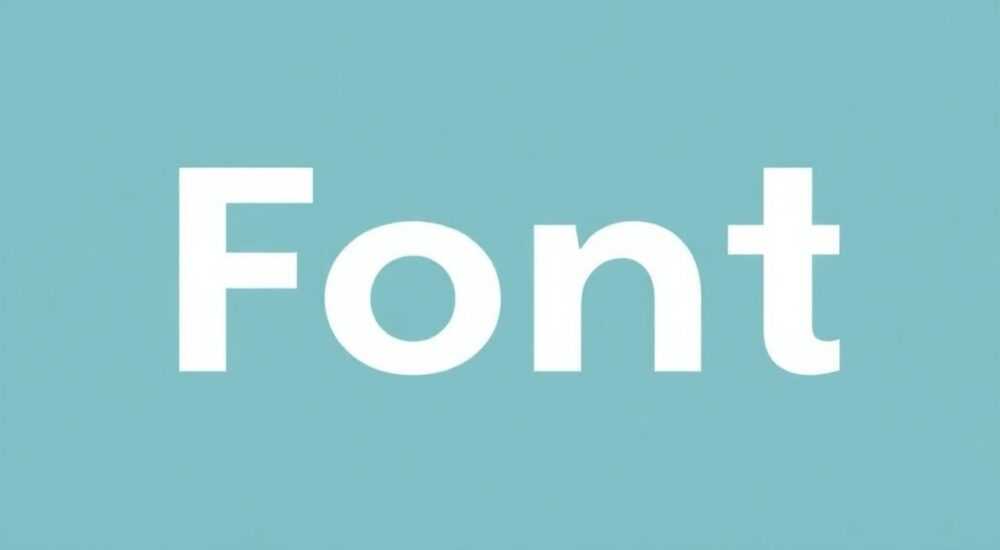
Как в фотошопе поменять шрифт
Изменение шрифта в Photoshop — одна из базовых, но крайне важных операций при работе с текстом на изображениях. Будь то редактирование баннера, создание макета для соцсетей или корректировка дизайна логотипа, умение быстро и точно заменить шрифт позволяет сохранить целостность визуального стиля. В отличие от простых графических редакторов, Photoshop предоставляет полный контроль над типографикой: от выбора гарнитуры до тонкой настройки интерлиньяжа и кернинга.
Основные шаги: как поменять шрифт в Photoshop
Замена шрифта в Photoshop начинается с правильного выделения текстового слоя. Откройте файл в программе и перейдите в палитру «Слои» (F7). Найдите слой с текстом — он будет обозначен значком «T» и называться, например, «Text» или содержать фрагмент текста. Дважды щелкните по этому слою, чтобы активировать режим редактирования.
Выберите инструмент «Текст» (горячая клавиша T). Кликните внутри текстового блока на холсте, чтобы появился текстовый курсор. В этот момент в верхней панели параметров активируется строка настройки шрифта. Здесь вы увидите выпадающий список с текущей гарнитурой.
Чтобы изменить шрифт, просто кликните по названию текущей гарнитуры и пролистайте доступные варианты. Вы можете начать вводить название шрифта вручную — Photoshop поддерживает поиск по имени. После выбора нового шрифта текст на холсте обновится мгновенно.
- Убедитесь, что текстовый слой не растрирован — иначе его нельзя будет редактировать как текст.
- Используйте сочетание Ctrl+Z (Cmd+Z на Mac) для отмены, если шрифт сместил разметку.
- Проверьте размер шрифта и межбуквенные интервалы — они могут меняться при смене гарнитуры.
Если текст состоит из нескольких абзацев или использует разные стили (жирный, курсив), выделите только ту часть, которую хотите изменить. Для этого зажмите Shift и выделите нужные символы мышью. Это особенно полезно при работе с заголовками и подзаголовками.
Пошаговая инструкция
- Откройте PSD-файл в Photoshop.
- Перейдите в палитру «Слои» и найдите текстовый слой.
- Выберите инструмент «Текст» (T).
- Кликните по тексту на холсте для активации редактирования.
- В верхней панели найдите поле «Шрифт» и выберите новую гарнитуру.
- При необходимости скорректируйте размер, цвет и выравнивание.
- Нажмите Enter (или кликните за пределами текста), чтобы применить изменения.
Работа с шрифтами в PSD-файлах: скрытые сложности
Один из главных вызовов при смене шрифта — это отсутствие нужной гарнитуры в системе. Когда вы открываете чужой PSD-файл, Photoshop может показать предупреждение: «Шрифт не найден». В этом случае текст автоматически заменяется на системный шрифт (часто Arial или Helvetica), что искажает дизайн.
Программа предлагает два пути: игнорировать проблему или заменить шрифт вручную. Игнорирование допустимо, если вы планируете всё равно менять гарнитуру. Но если нужно сохранить оригинальный стиль, следует установить недостающий шрифт.
Photoshop запоминает исходный шрифт даже при его отсутствии. При наведении на текстовый слой в палитре «Слои» вы можете увидеть название шрифта серым полупрозрачным текстом — это означает, что он недоступен. При выборе такого слоя в верхней панели также отобразится сообщение «[шрифт недоступен]».
Другая проблема — масштабирование текста. Разные шрифты имеют разную оптическую плотность и высоту строчных букв. Например, при замене Roboto на Georgia текст может «расползтись» по ширине или «съехать» по высоте, нарушая выравнивание.
Шрифт |
Средняя ширина символа (px при 16pt) |
Высота x (относительная) |
Риск смещения макета |
Roboto |
9.8 |
0.58 |
Низкий |
Georgia |
11.2 |
0.45 |
Средний |
Montserrat |
10.1 |
0.62 |
Низкий |
Times New Roman |
10.8 |
0.43 |
Высокий |
Как минимизировать искажения при смене шрифта
- Перед заменой сделайте снимок состояния макета (Ctrl+Alt+Shift+E).
- Используйте шрифты из одной категории (например, все геометрические grotesque sans-serif).
- Настройте кернинг и трекинг вручную, если текст «поехал».
- Проверьте поведение текста на разных разрешениях и экранах.